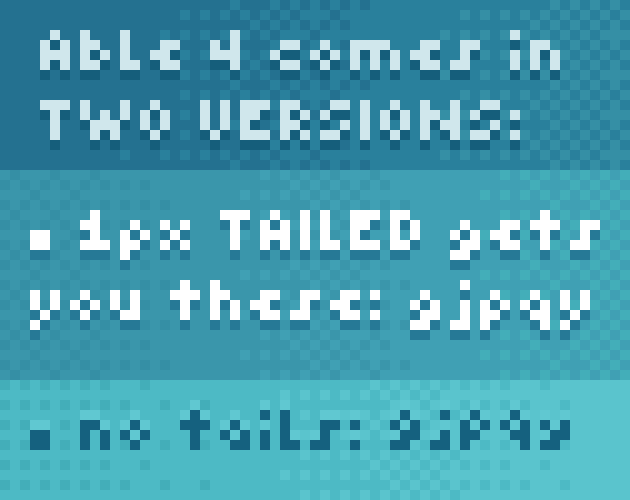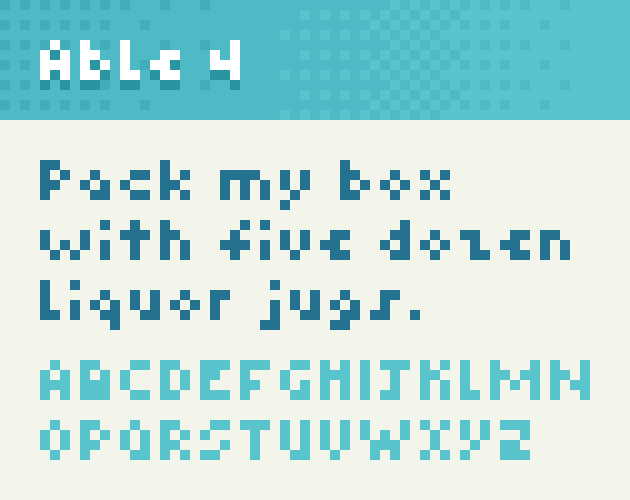
较小的Able 4像素字体素材,Able 4 是 Able 字体家族中更小巧的版本。
大写字母高度仅为 4px,可以适应大多数其他字体无法适应的位置!此外,它还提供了带下降线的版本,看起来更美观,但底部需要额外留出 1px;如果您空间不足,还可以选择不带下降线的版本。
它支持的语言远不及Able 5多,但它支持西里尔字母和希腊字母,以及一些带重音的罗马字母。